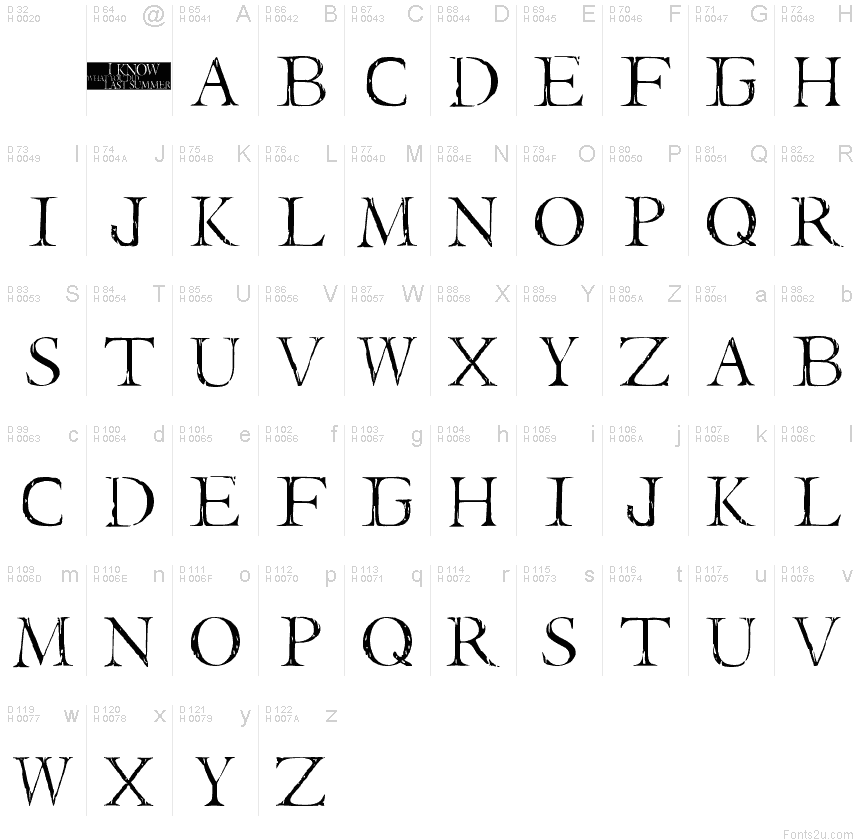
I Still Know autorstwa Thomasa W. Otto to darmowy, mroczny krój szeryfowy o postarzanym wyglądzie. Wysokie, kruche litery wyglądają, jakby zostały wydrapane w kamieniu, z poszarpanymi krawędziami i atramentowymi prześwitami, które budzą niepokój, ale nie sprawiają wrażenia niechlujstwa. Odstępy pozostają ciasne i kontrolowane, dzięki czemu nawet przy całym tym efekcie rozkładu, słowa pozostają ostre, czytelne i złowieszcze – niczym wyszeptana groźba, o której nie sposób zapomnieć.
Dzięki I Still Know nadasz tytułom horrorów, okładkom thrillerów, plakatom na Halloween, oprawie graficznej escape roomów, logotypom gier czy mrocznym okładkom albumów prawdziwie chłodny klimat. Ten darmowy font świetnie sprawdza się w dużych nagłówkach, gdzie popękane kreski mogą w pełni wybrzmieć. W tekście głównym połącz go z czystym, dyskretnym bezszeryfowym krojem, aby zachować czytelność przy jednoczesnym utrzymaniu groźnego charakteru.